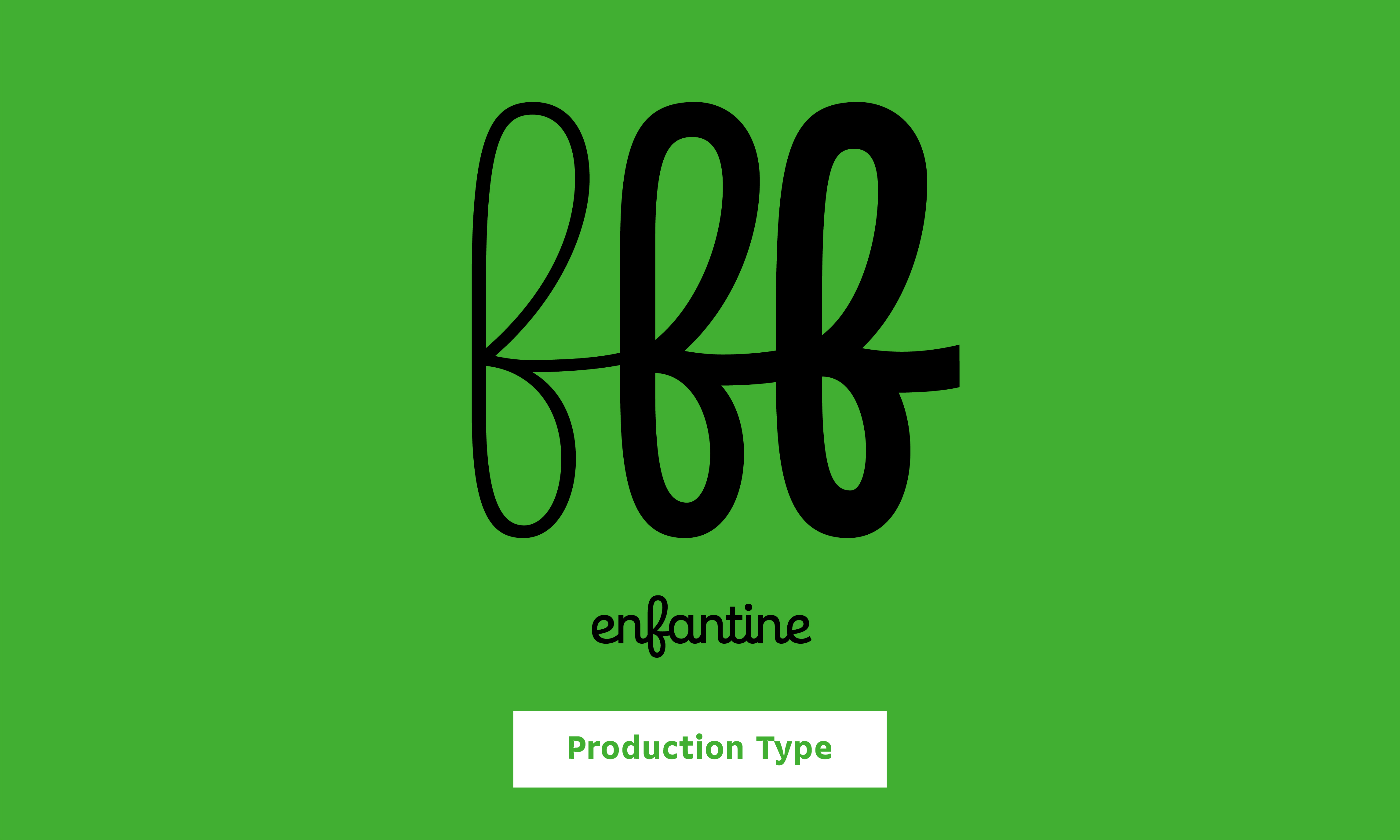
Enfantine
Enfantine는 필기체 손글씨를 바탕으로 하는 친숙하고 정감가는 디자인의 폰트이다.
필기체를 바탕으로 한 만큼 자연스럽게 글자와 글자 사이가 연결되는 것이 특징이며, 실용적이면서도 현대적인 디자인 덕분에 문맥 안에서도 폰트 본연의 기능을 잘 발휘할 수 있다.
- Ben Kiel Jean-Baptiste Levée Loïc Sander Yoann Minet Yohanna My Nguyen
- Script